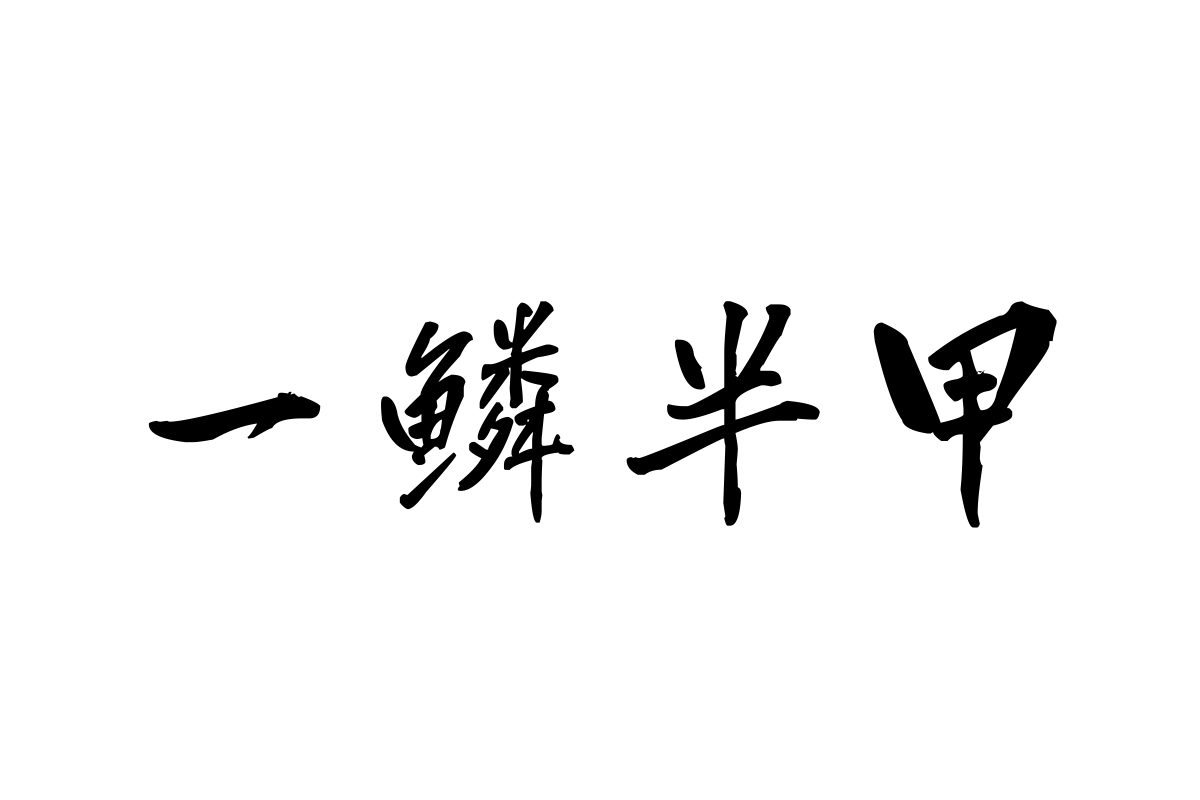
汉标儒雅楷书是一套由汉标公司开发的中文字体,旨在为中文用户提供一种优雅、易读的书法风格。这款字体以其传统的楷书风格为基础,融入了现代设计元素,使其在保持传统美感的同时,也更加适合现代的设计需求。
汉标儒雅楷书的特点包括:
1. 字形结构:该字体采用了传统的楷书字形结构,笔画清晰,易于辨识。同时,通过调整笔画间距和粗细,使其更适合现代的设计需求。
2. 设计风格:汉标儒雅楷书注重整体风格的统一,无论是标题、正文还是装饰性文字,都能呈现出优雅、大方的气质。此外,该字体还具有一定的艺术感,能够为设计作品增添独特的韵味。
3. 应用场景:汉标儒雅楷书适用于各种类型的设计项目,如海报、宣传册、网页设计等。它能够很好地与各种背景和色彩搭配,使设计方案更加出色。
总之,汉标儒雅楷书是一款具有传统书法风格和现代设计元素的中文字体,适用于多种设计场景,能够满足用户对优雅、易读字体的需求。